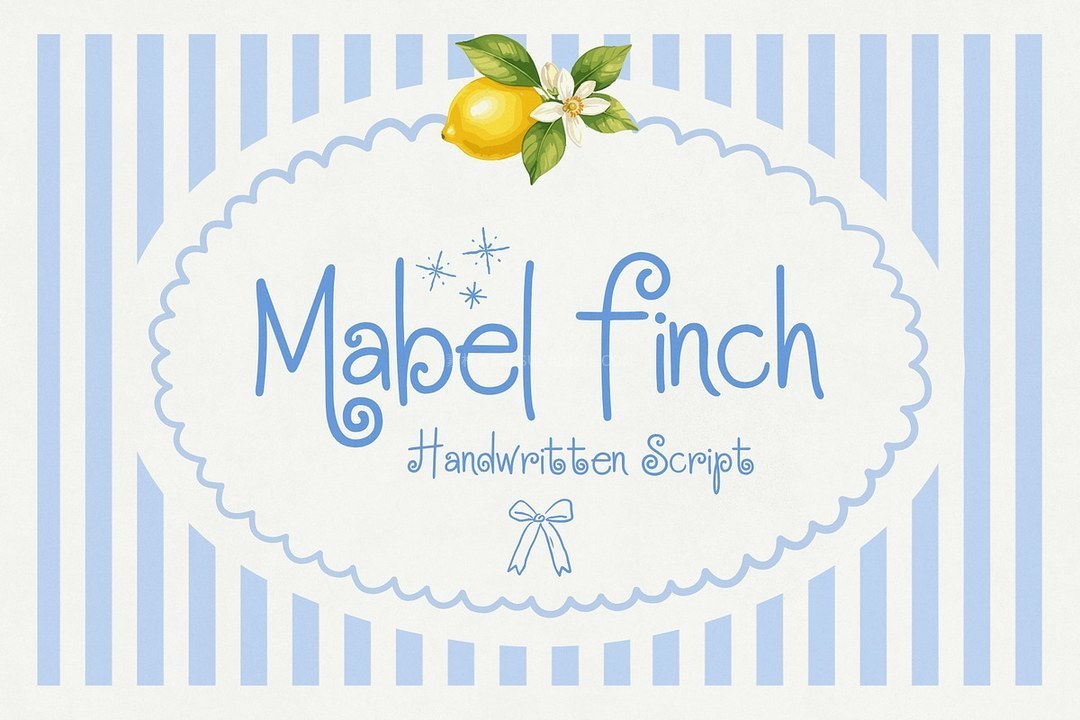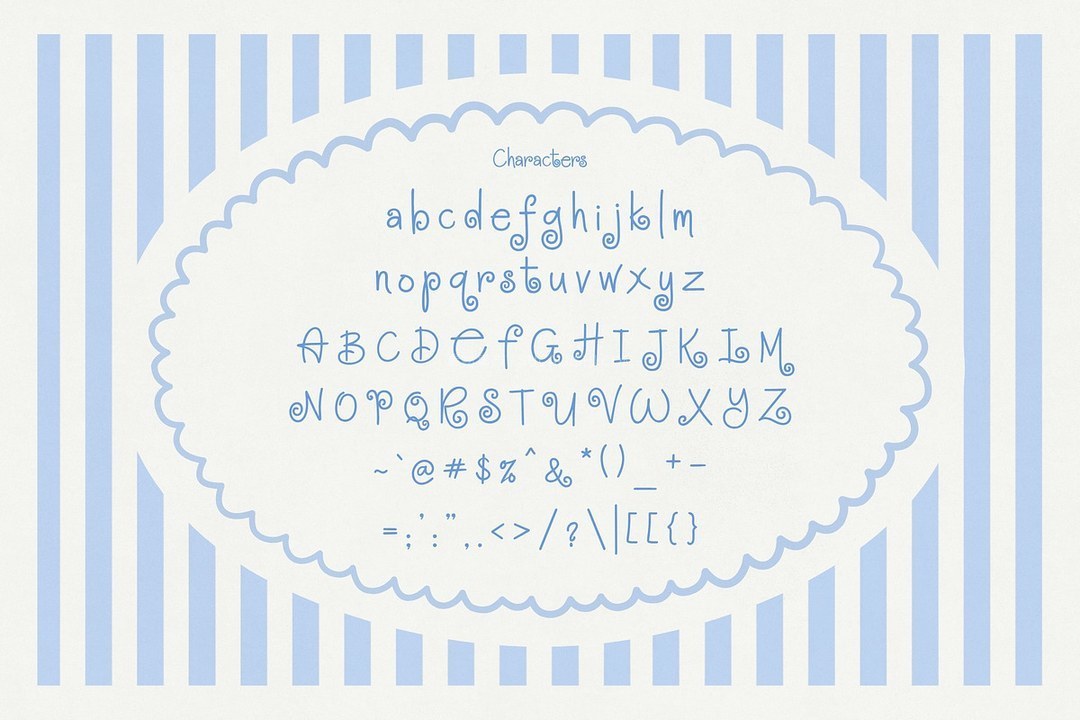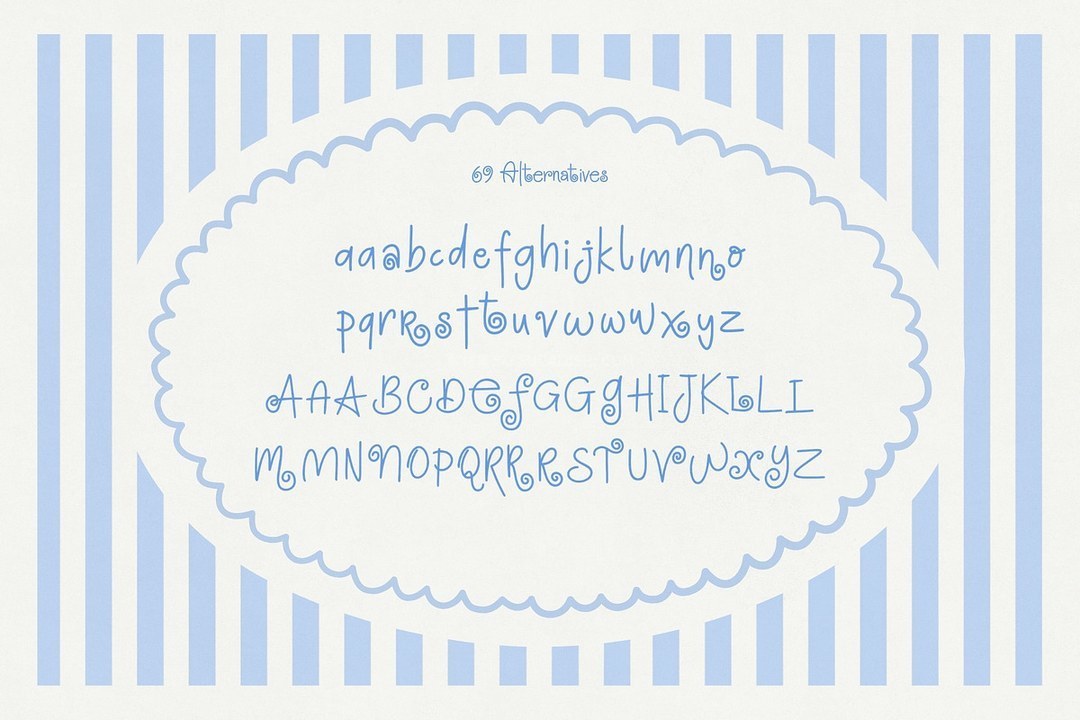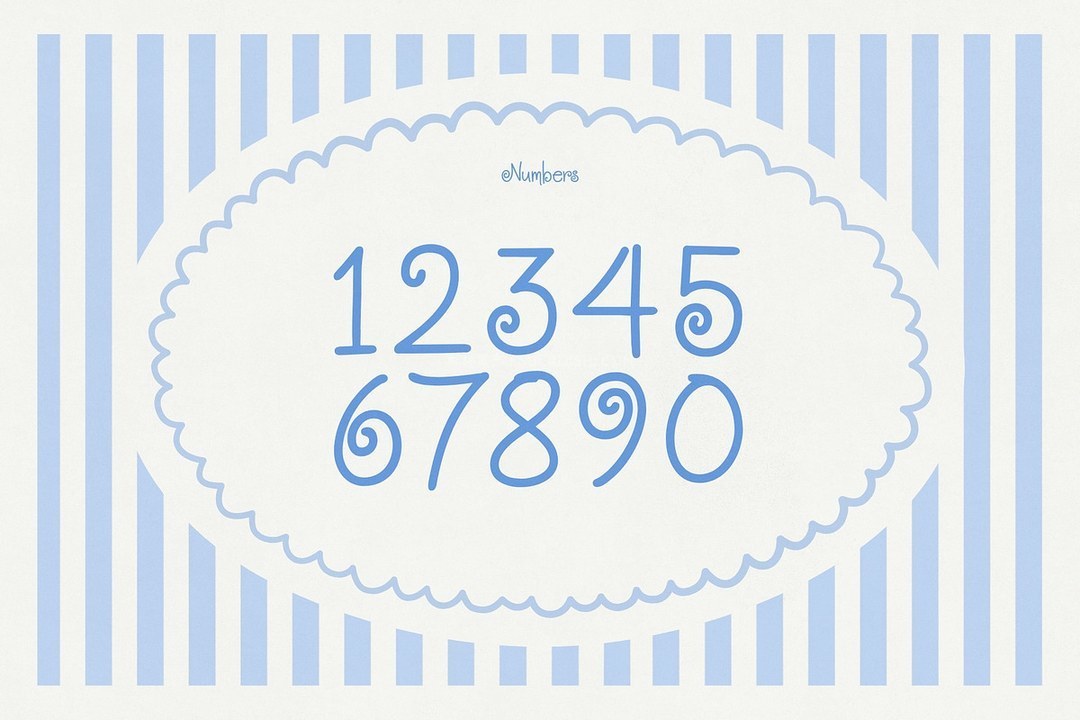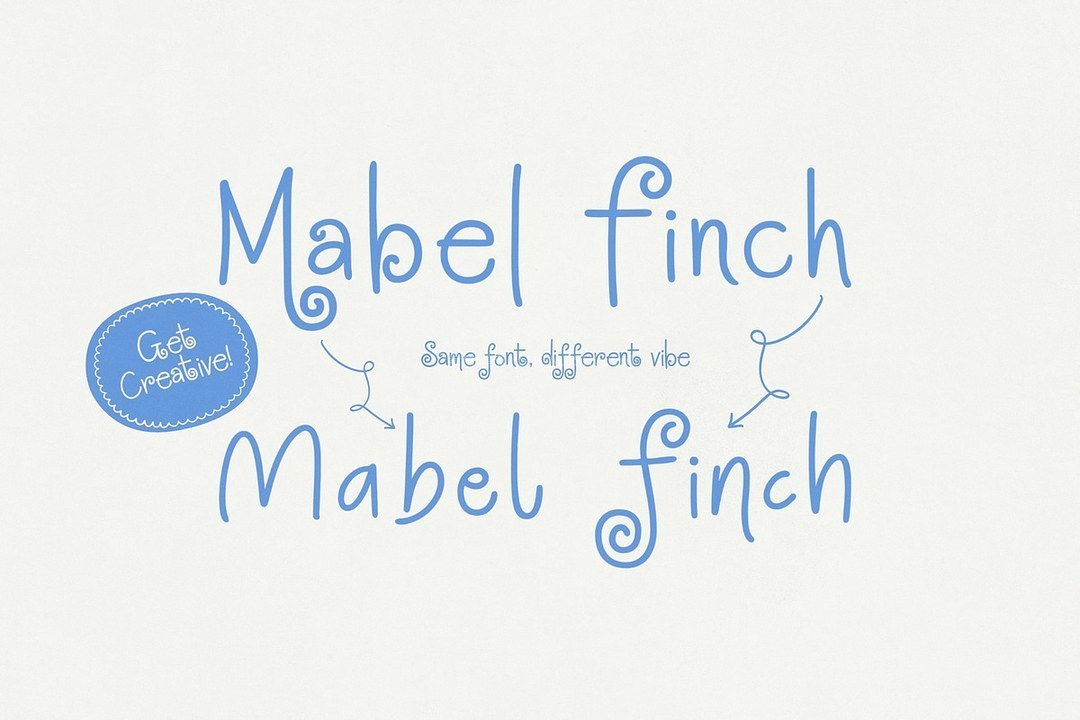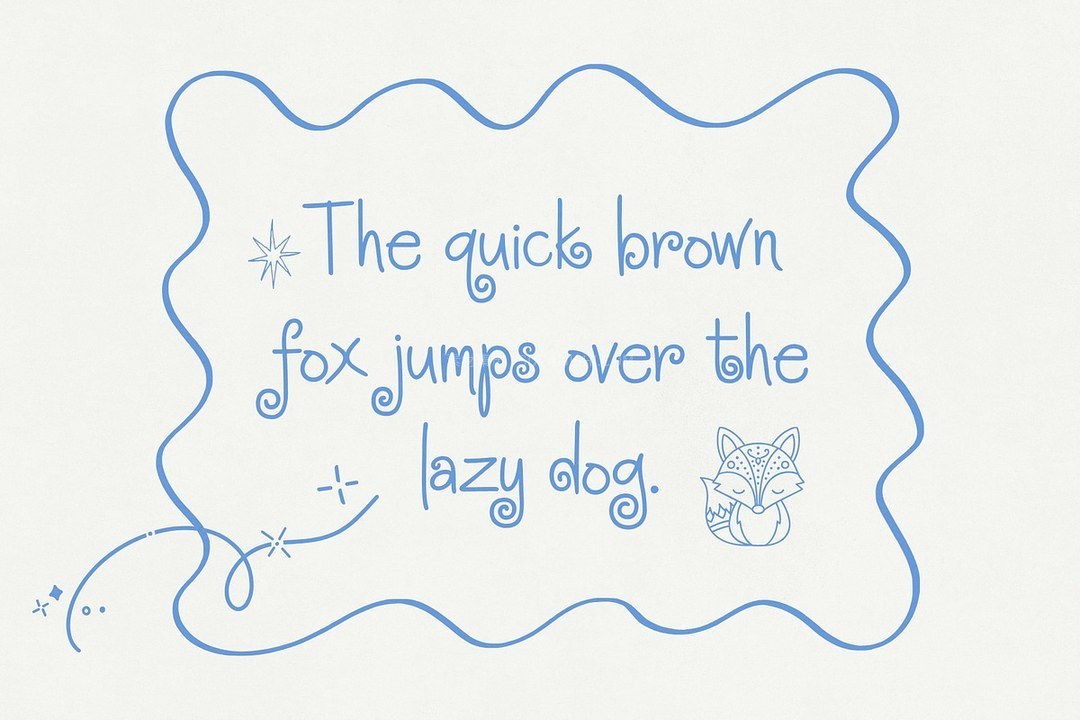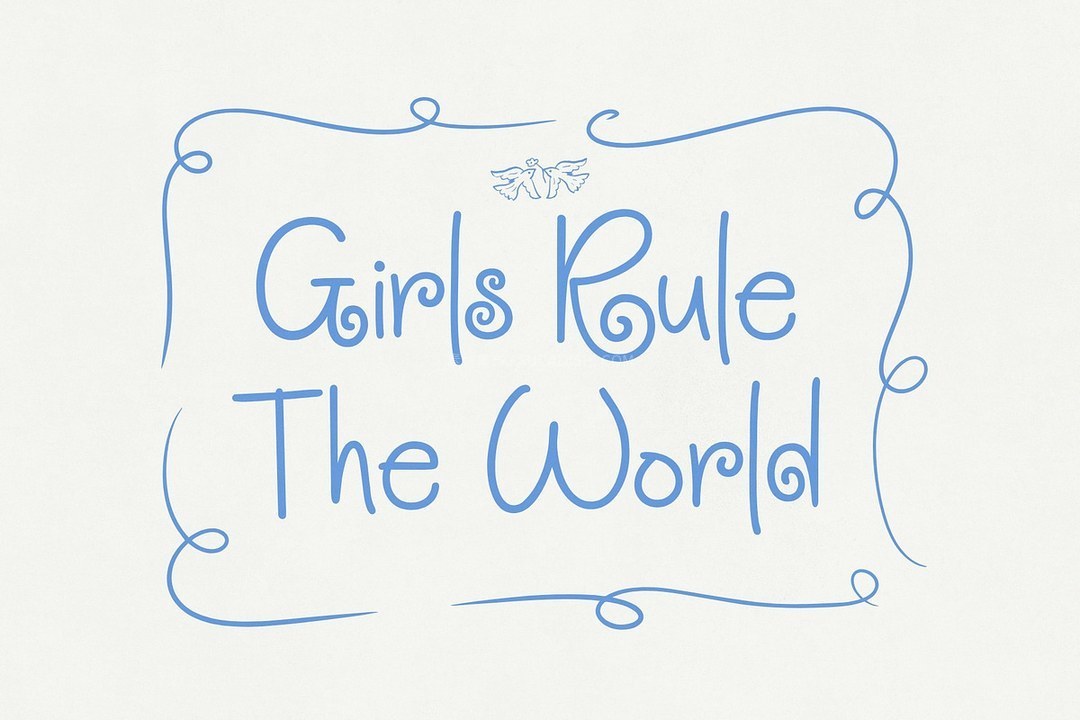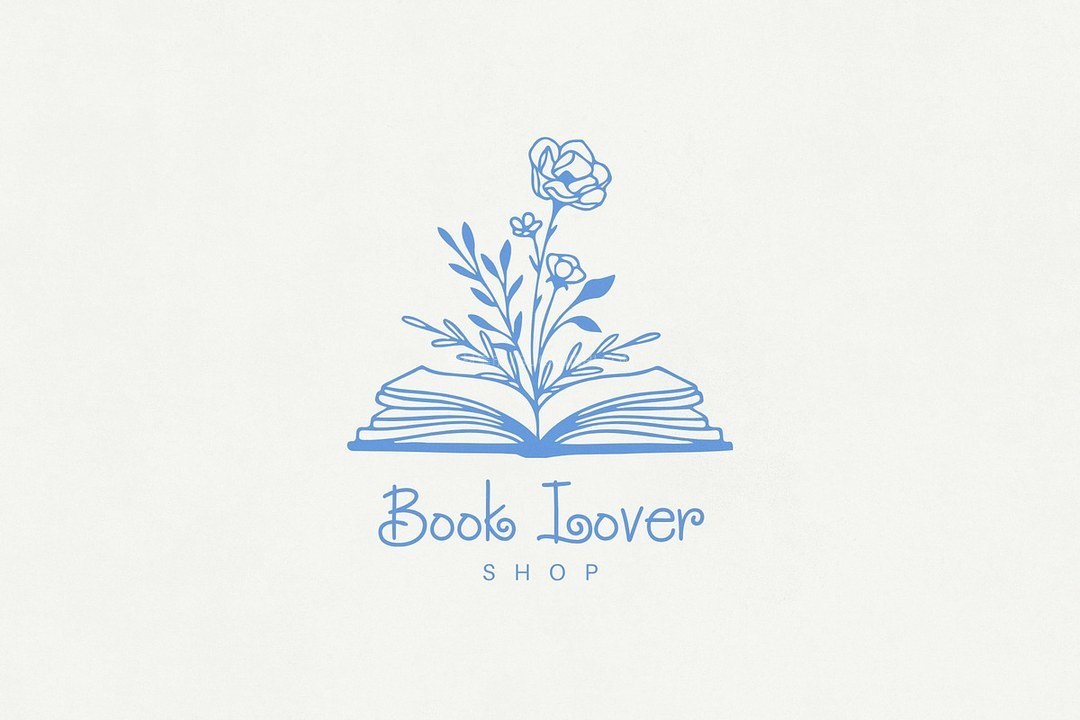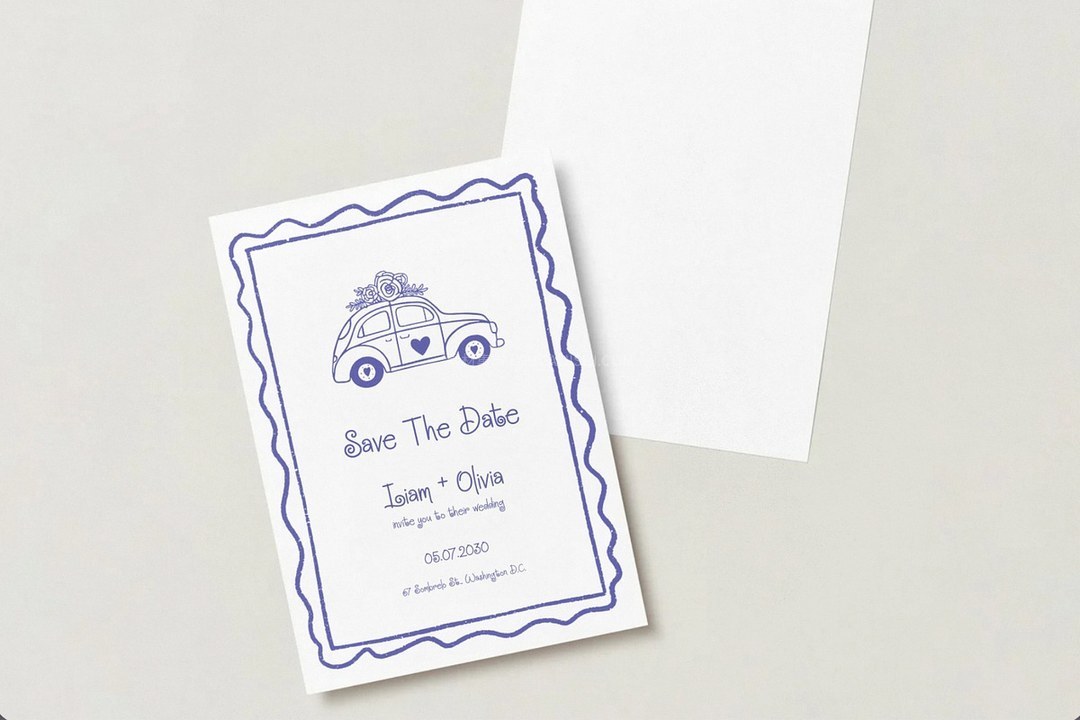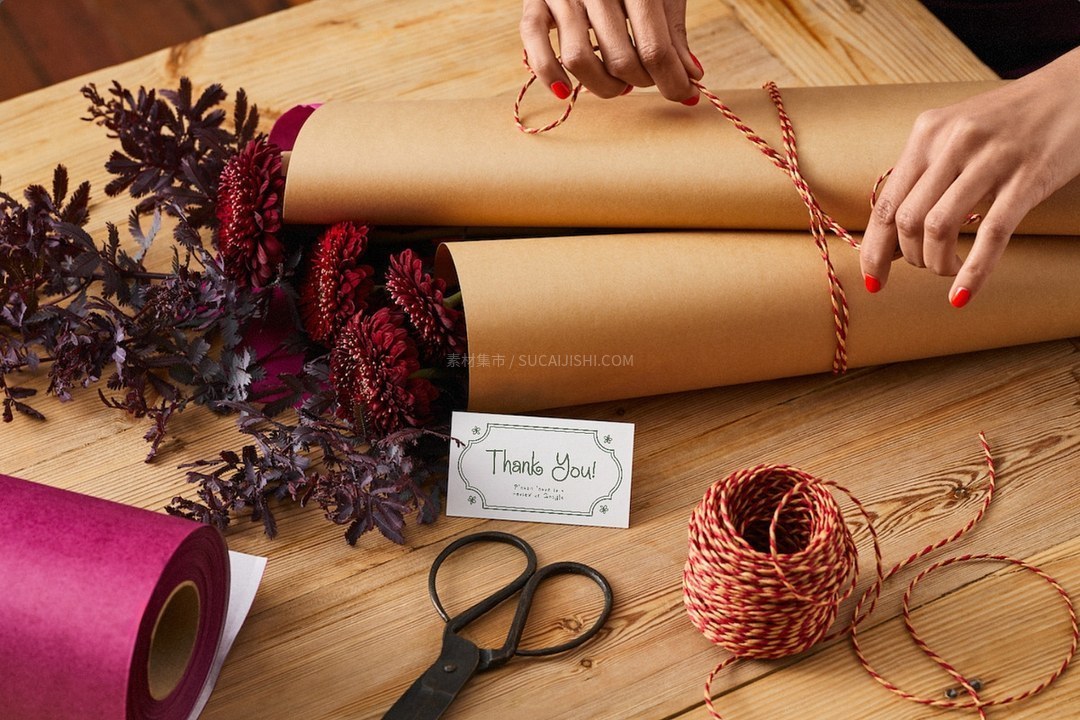
Mabel Finch趣味手写英文字体
Mabel Finch 是一款充满趣味的手写字体,线条柔和流畅,笔画纤细,字形独特,细节之处尽显妩媚。它巧妙融合了怀旧情怀与现代百搭风格,奇趣的造型与复古设计完美契合,而简洁精致的结构又使其同样适用于现代精品店、创意企业、手工艺品和个性化文具。无论是打造令人着迷的精品店标志、产品包装、蜡烛标签,还是婚礼请柬、贺卡与社交媒体设计,Mabel Finch 都能将普通的文字转化为充满个性、令人愉悦且独一无二的作品。